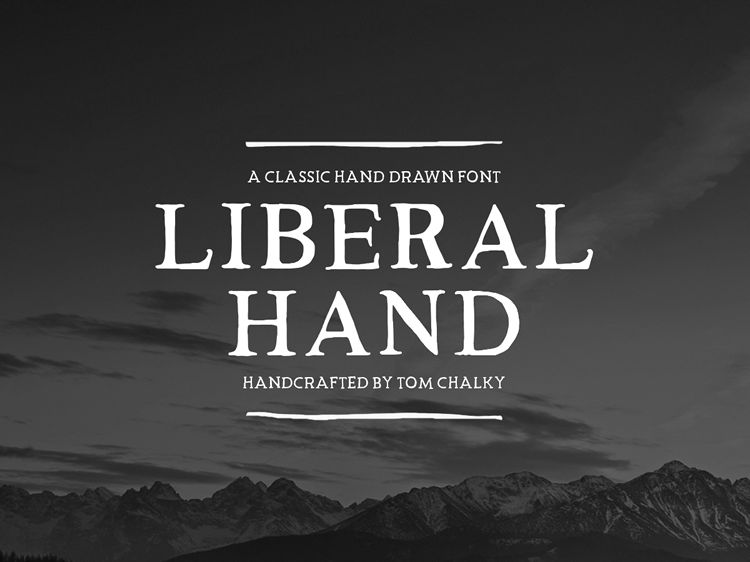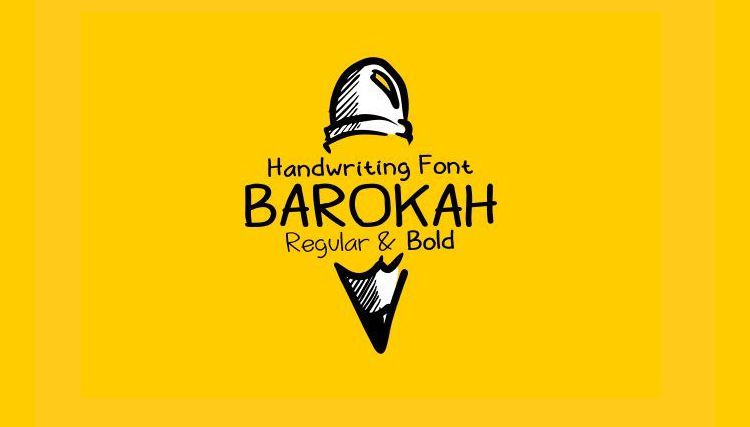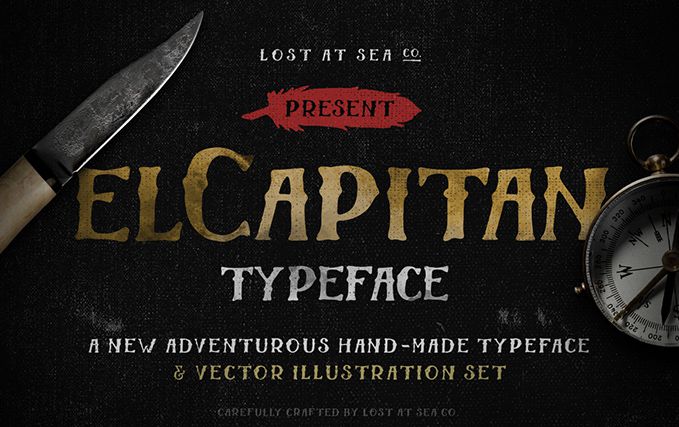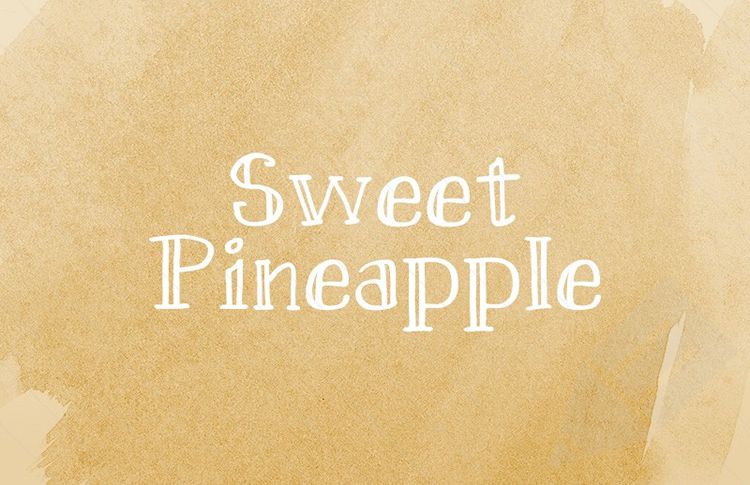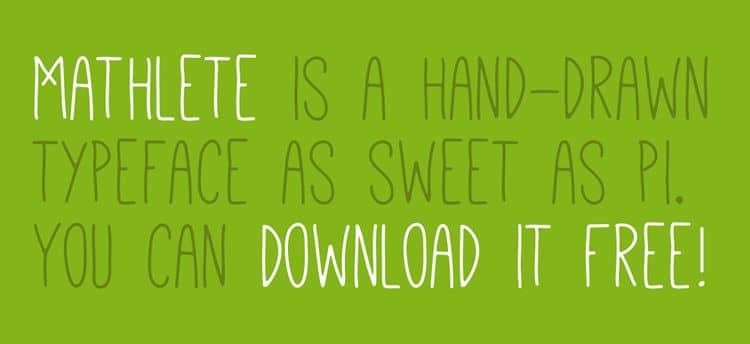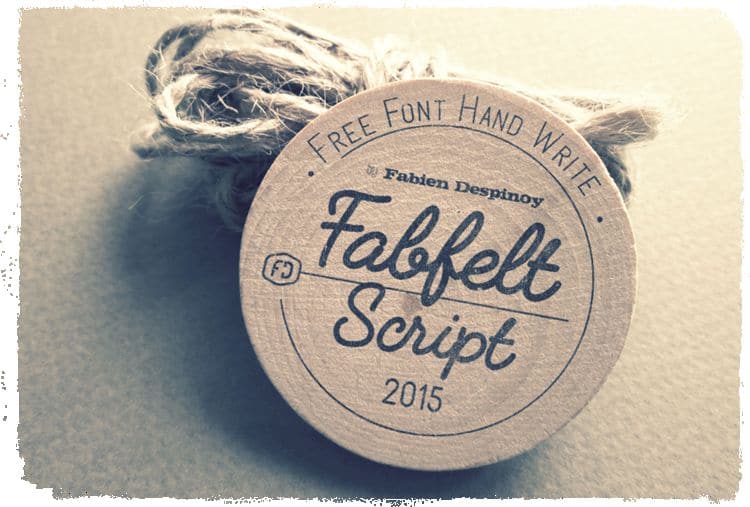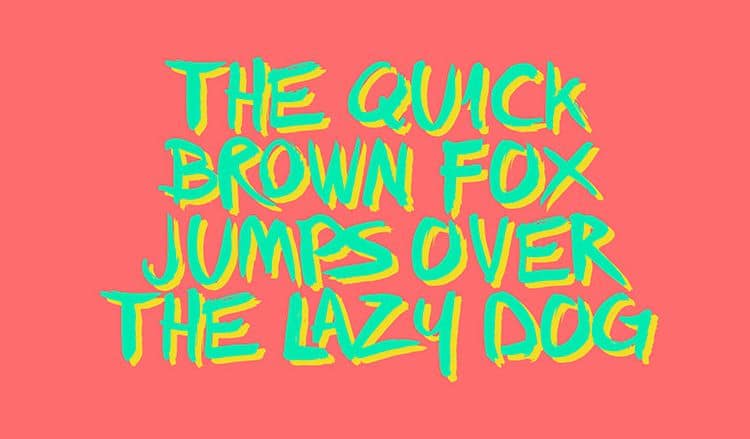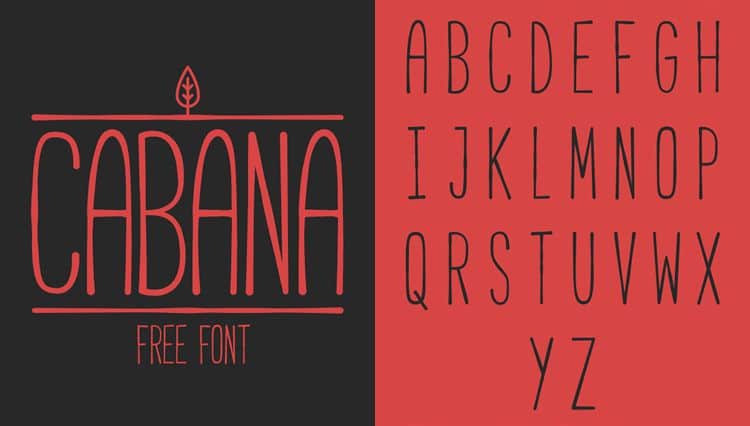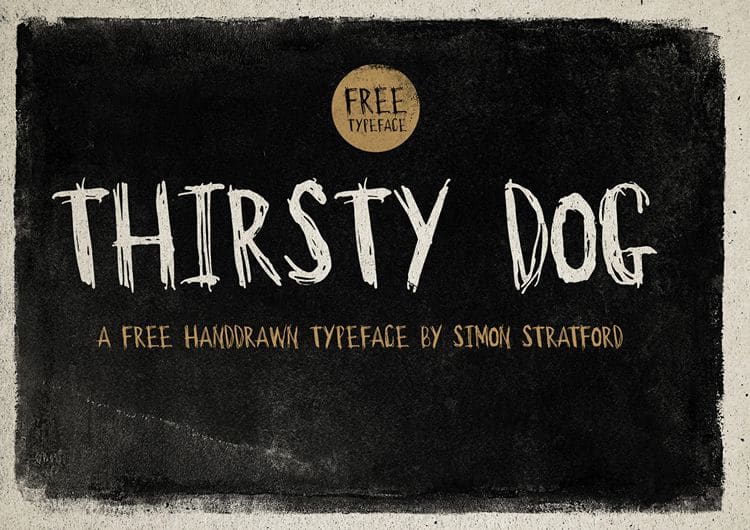
Bellas fuentes tipográficas manuscritas ( Handdrawn) o hechas a mano gratis
Si usted mira a los diseñadores nunca les es suficientes, la librería de fuentes en sus herramientas. Y las fuentes dibujadas a mano son una  elección perfecta si desea agregar un poco de encanto y toque personal a su trabajo.
Con el uso y el buen gusto, las fuentes manuscritas o dibujadas a mano pueden dar a sus diseños un estilo y un toque de elegancia añadidos.
En esta colección, Les presento 19 de mis fuentes manuscritas favoritas. ¡Estamos seguros de que las amarás!
En Speckyboy han realizado una recopilación de mas de 20 espectaculares fuentes tipográficas conocidas como Handdrawn Fonts, y constantemente actualiza los recursos  y muestra  ejemplos de uso aplicados a imágenes que te pueden  inspirar y los mas seguro que te impulsa  a contar con cada una de ellas.
Fuentes gratuitas dibujadas a mano o handdrawn:
Carosello Font
Carosello free handwritten Font
Arabella Free Font
Arabella free handwritten Font
Waterlily Free Handwriting Font
Waterlily free handwritten Handwriting Font
Breathe Font Family
free handwritten Breathe Font Family
MAZAK Font
MAZAK Font family handwritten
Nickainley Handwriting Font
free Nickainley Handwriting Font
Cutepunk Typeface – Light, Regular & Bold – By Cutepunk (OTF)
free font Cutepunk Typeface
Barokah Uppercase & Lowercase Display By Graptail Design (OTF)
Barokah Uppercase font free Lowercase Display
El Capitan Hand-Drawn Font By Petr Knoll (OTF & AI)
El Capitan Hand-Drawn free Font
Sweet Pineapple Hand-Drawn Serif By Medialoot (OTF & Web Font)
Sweet Pineapple Hand-Drawn free Serif
Mathlete Hand-Drawn Font – Skinny, Slant, Bulky & Bulky Slant – By Mattox (OTF & Web Font)
Mathlete free Hand-Drawn Font
Liberal Hand Serif Font – Regular & Bold – By Tom Chalky (OTF & TTF)
Liberal Hand Serif Free Font
Bough Hand-Drawn Typeface By Pavel Korzhenko (OTF)
Bough Hand-Drawn Typeface free font
Fabfelt Handwritten Script – Bold – By Despinoy Fabien (OTF & Web Font)
Fabfelt Handwritten Script free font
FFAD Matro Handwritten Font By SuperBruut (TTF & Web Font)
FFAD Matro Handwritten free Font
CABANA Handmade Font By Adrien Coquet (OTF)
CABANA Handmade free Font
Refuge Handcrafted Typeface By Grant Beaudry (OTF)
Refuge Handcrafted Typeface free
Thirsty Dog Handdrawn Typeface By Simon Stratford (OTF)
Thirsty Dog Handdrawn free Typeface
Monthoers Handmade Letterpress By Agga Swist’blnk (TTF)
Monthoers Handmade free font Letterpress